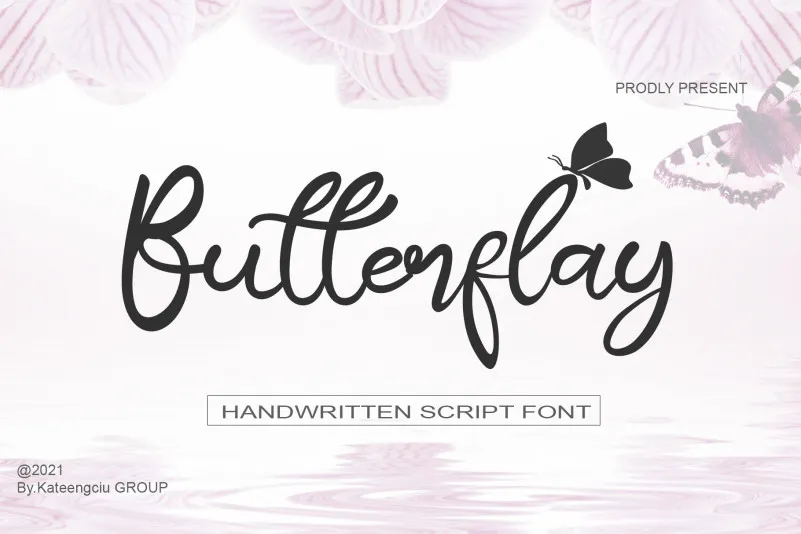
A Butterflay Script Font é uma escolha ideal para designers que buscam algo único no seu trabalho, mas ainda desejam manter um toque elegante e sofisticado. Embora mantenha seus lindos traços de calligrafia tradicionais, esta fonte também se mostra atual e inovadora. Suas capacidades multifuncionais garantem que esteja sempre à altura das últimas tendências gráficas, sendo perfeita para uma variedade incrível de projetos. Esta fonte será adorada por designers que desejam criar um conjunto de letras atraente e elegante, ou qualquer outro projeto onde desejas dar um toque pessoal. Ela é particularmente útil para trabalhos envolvendo cartões postais, assinaturas, identidades visuais e até mesmo estilização de textos em sua própria página web. Composta por um designer talentoso, Kateengciu, a Butterflay Script Font traz uma qualidade única que impressionará seus clientes. Este design é perfeito para quem procura uma fonte casual e elegante para complementar seu trabalho artesanal ou personalizado. Aqui está uma maneira de destacar o seu trabalho com um toque único sem abrir mão do glamour tradicional, tornando esta fonte uma ótima escolha para qualquer projeto que deseja dar a sua identidade pessoal.